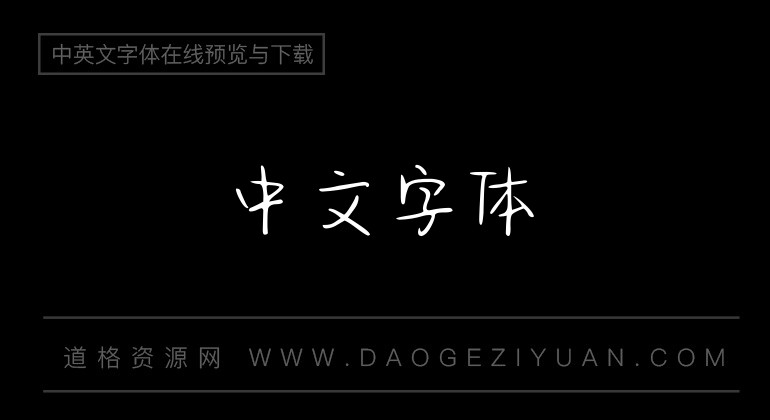
Aa放课后下午茶
Aa放课后下午茶是一款字体,它采用了现代感的设计,以及细腻的笔触,给人以清新、舒适的感觉。它的字体特点是细腻的笔触,这使得它看起来更加柔和,更加优雅,令人耳目一新。它的字形设计简洁,适合用于各种类型的文档,以及各种类型的设计,可以满足不同的需求。
Aa放课后下午茶是一款非常不错的手写艺术字体,具有很好的视觉感,适合于文化类的宣传设计、商业类品牌的广告和产品包装设计以及个性化文字排版等较多场景。